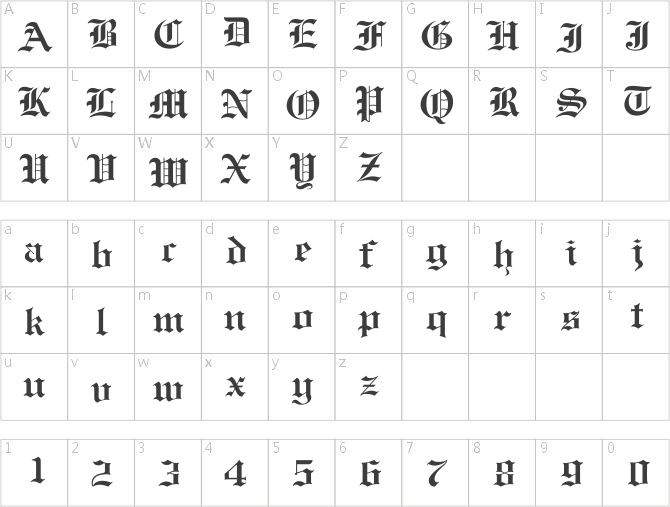
MEngraversOldEnglish-Wd
MEngraversOldEnglish-Wd介绍
MEngraversOldEnglish-Wd字体字库是一款让人赏心悦目、百看不厌的英文字体,适合各类广告和产品包装设计应用,字体大小0.19MB,格式为ttf字体,上传用户是Who am I?,作者/版权方为未知